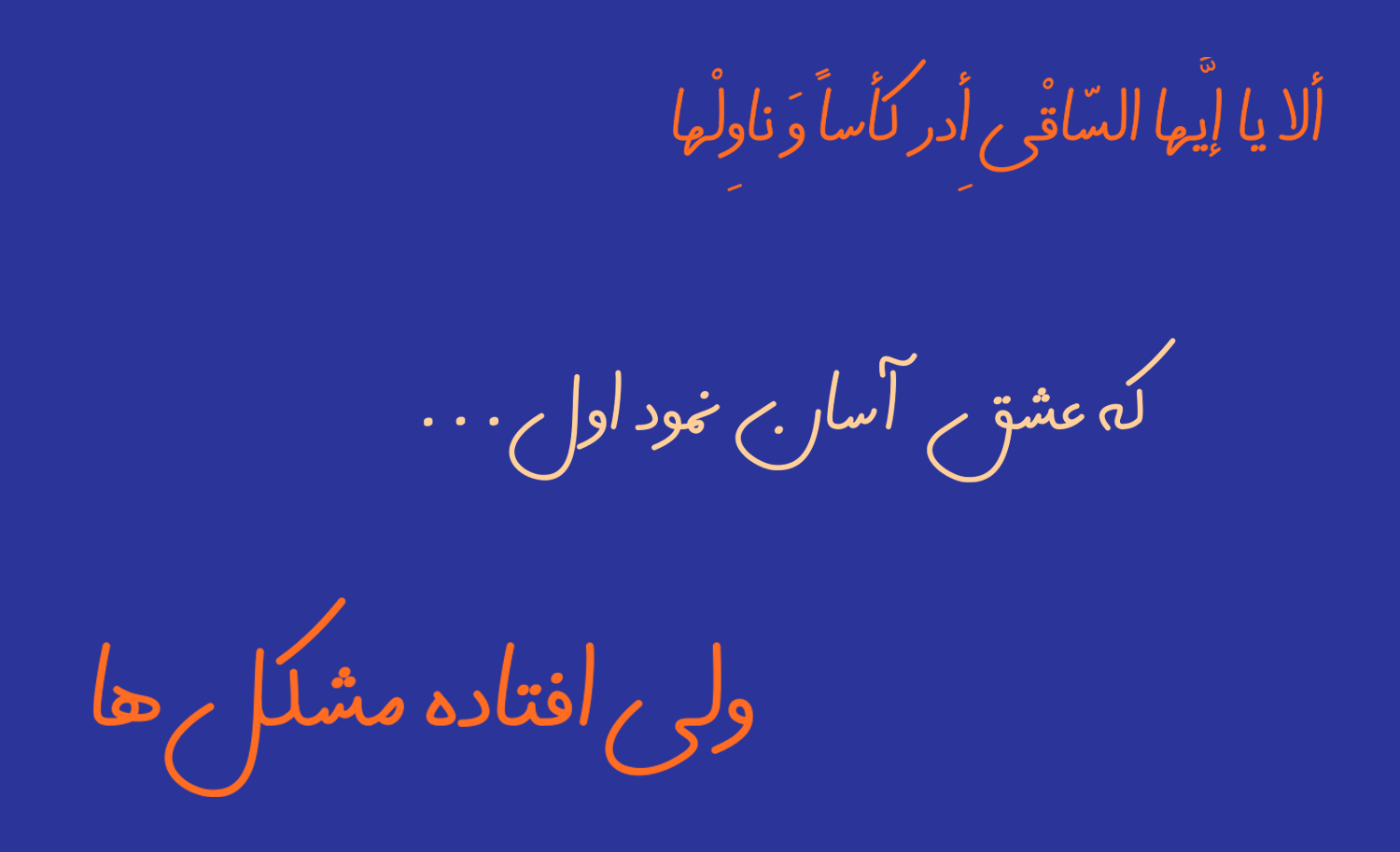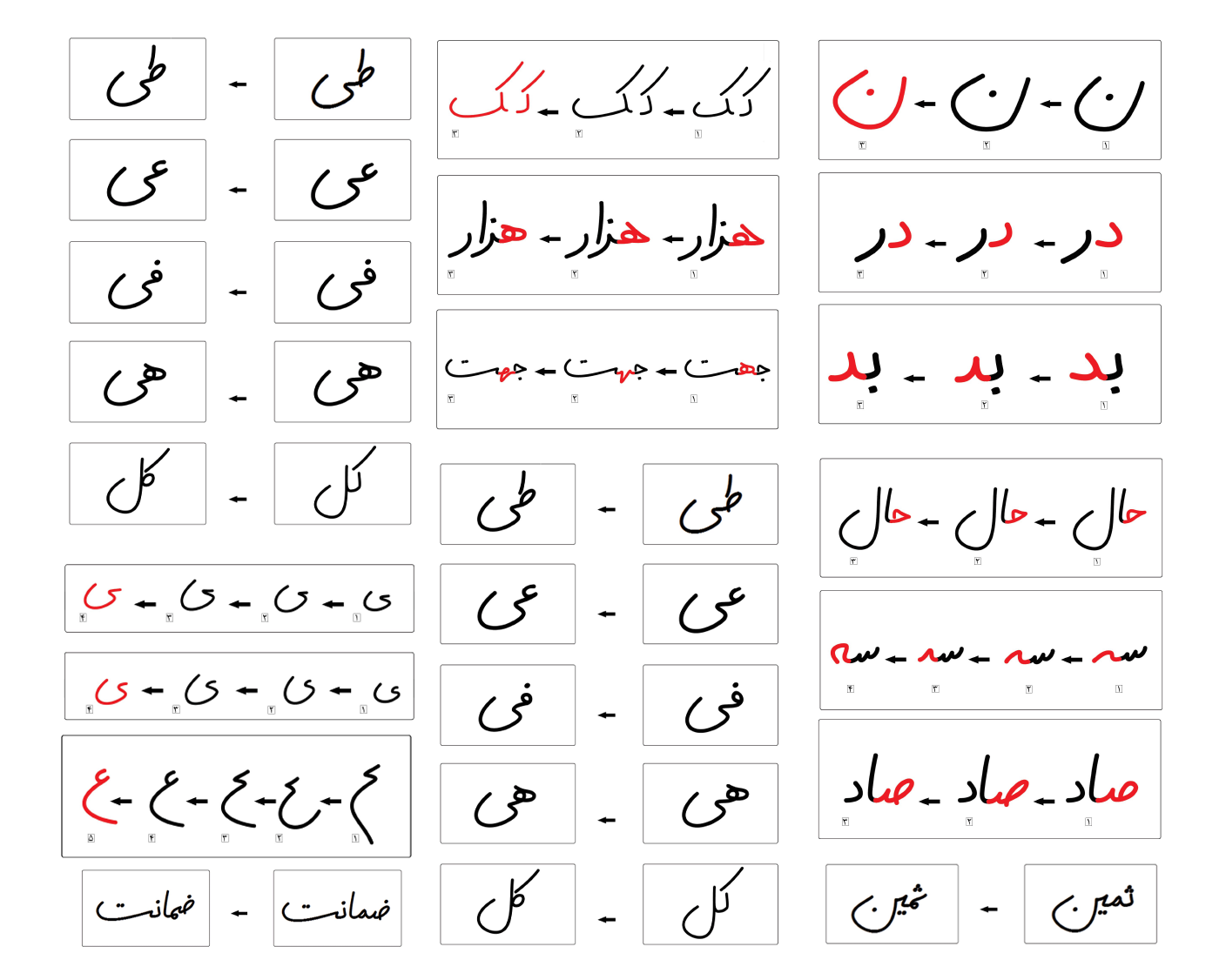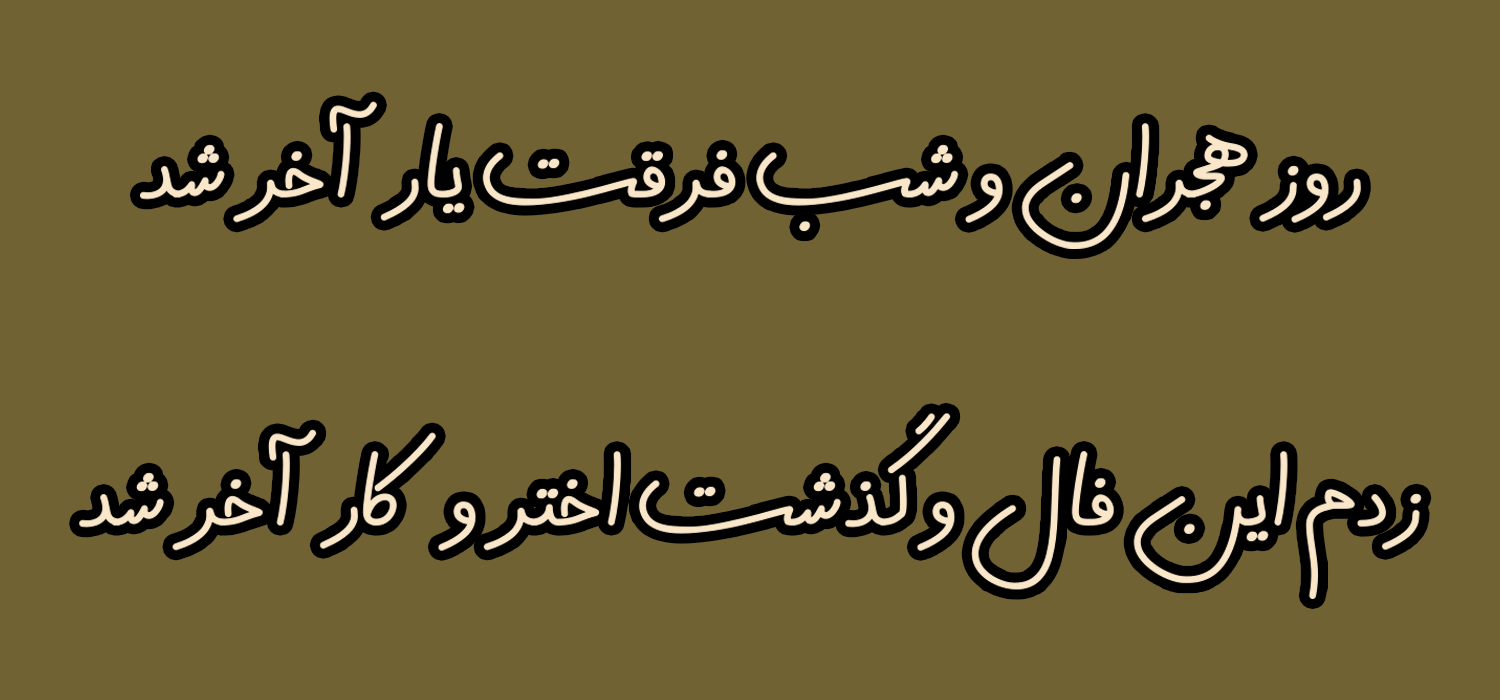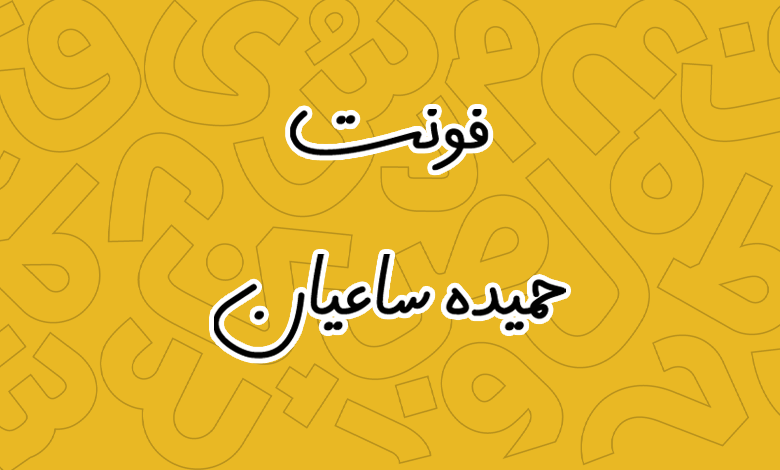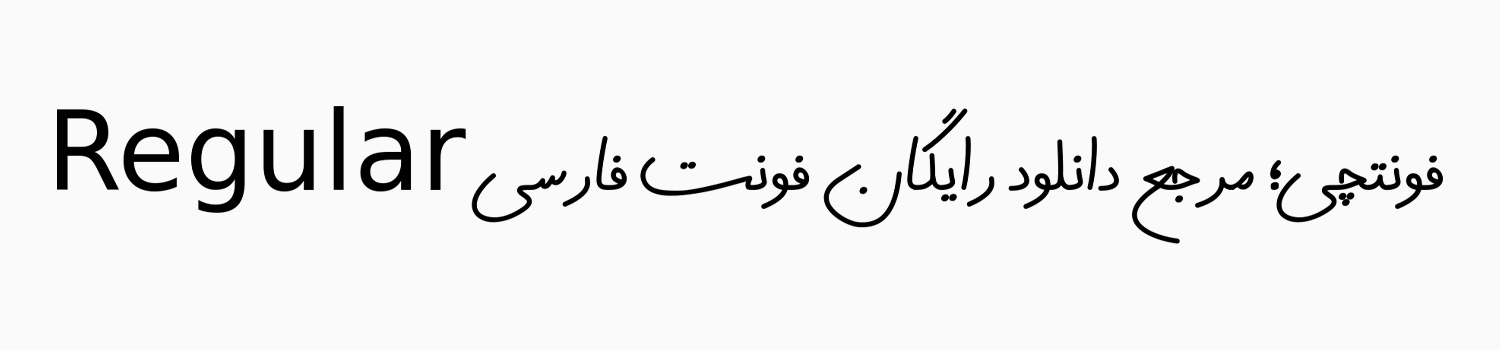
فونت حمیده ساعیان (Hamideh Saeian)
فونت حمیده ساعیان (به انگلیسی: Hamideh Saeian) در گروه فونت دست نویس قرار دارد که می‌توانید از آن برای متن‌های طولانی استفاده کنید. این قلم را همچنین می‌توان در گروه فونت خودکار نیز طبقه‌بندی کرد، چرا که بر اساس دست‌خط شخصی طراحی شده است.
حمیده ساعیان این قلم را بر اساس دست‌خط شخصی خود طراحی کرده که در مقایسه با سایر فونت‌های دست نویس خودکاری، آزادی شکل و تنوع بیشتری به حروف و ترکیبات را در این قلم پیاده‌سازی کرده است که می‌تواند برای استفاده‌های تبلیغاتی، فرهنگی و هنری، فضاهای صمیمی و شاعرانه کاملا ایده‌آل باشد.
در ادامه این نوشته از سایت فونتچی به نقد و بررسی کامل فونت حمیده ساعیان خواهیم پرداخت؛ قلمی به سبک دست نویس خودکاری که در یک وزن معمولی Regular در دسترس بوده و می‌توانید از آن در انواع نرم‌افزار گرافیکی و ویرایشگر متن با پشتیبانی کاملی که از دو زبان فارسی و عربی دارد استفاده کنید.
جدایی از اینکه این فونت، یک قلم صمیمی و بر اساس دستخط شخصی است؛ شکل خاص و آزادی که به حروف در این قلم داده شده آن را به گزینه‌ای عالی برای فضاهای تبلیغاتی بدل کرده است. امکان استفاده از ترکیبات متنوع برای حروف سبب می‌شود تا بتواند برای نکته نویسی در تبلیغات انتخاب خوبی باشد.
سبک طراحی و وزن فونت ساعیان
در این فونت طراح بر اساس دستخط شخصی خود ابتدا حروف را طراحی کرد و سپس به منظور نمایشی و زیباتر کردن تمامی حروف و ترکیبات سعی شده تا از خوشنویسی به روح این قلم دمیده شود که انصافا خوب هم عمل کرده است.
با این کار شکل حروف از حالت خامی خارج شده و جدایی از اینکه فرم حروف به بهترین شکل پیاده‌سازی شده است، موجب نرم‌تر شدن و صمیمی تر شدن ساختار کلی قلم شده است.
پشتیبانی کامل از دو زبان فارسی و عربی
فونت ساعیان از دو زبان فارسی و عربی پشتیبانی تقریبا کاملی دارد. تمامی حروف که به صورت مشترک در این دو زبان قرار دارند در آن پیاده سازی شده است و شکل استاندارد هم را دارند.
اما حروفی که در زبان عربی متفاوت از زبان فارسی است، مانند «ک، ی، ه، ؤ، ئ» دارای گلیف اختصاصی خود هستند که هنگام استفاده از زبان عربی این ظاهر متفاوت روی حروف اعمال و تایپ می‌شود.
اعراب نیز در هم‌نشینی درستی با سایر اعراب همچون همزه، تشدید و سکون قرار دارند که نه به حروف قبل و بعد می‌چسبند و نه اینکه فاصله آنها در هنگام استفاده ترکیبی در تضاد زیادی با یکدیگر قرار دارد.
در بخش اعداد نیز این فونت با اینکه یک فونت دست‌نویس و بر اساس دستخط شخصی طراح است، اعداد فارسی و عربی را به شکل جداگانه پشتیبانی نمی‌کند. برای زبان فارسی به جای شکل استاندارد اعداد «۴۶» از شکل عربی آن یعنی، «۴۶» استفاده شده است و در مقابل برای عربی نیز به جای عدد «۵» از حالت فارسی آن یعنی «۵» استفاده شده است.
زبان انگلیسی در این فونت دارای طراحی دست نویس نبوده و از همان ساختار معمولی برای حروف لاتین استفاده می‌شود که پیشنهاد می‌کنیم از طریق صفحه فونت دست نویس انگلیسی فونت دیگری را در صورت استفاده ترکیبی از دو زبان در متن خود در نظر بگیرید.
دارای حروف و ترکیبات جایگزین بسیار متنوع
ویژگی متمایز این فونت در مقایسه با سایر فونت‌های دست نویس که ساختاری خودکاری دارند، پشتیبانی از حروف و ترکیبات جایگزین بسیار متنوع است که امکان تایپ کلمات را در چند حالت مختلف فراهم می‌کند. چنین ساختاری را پیش از این در فونت مانلی مشاهده کرده‌ایم.
همانطور که در تصویر بالا می‌بینید این‌ها تنها بخشی از ترکیبات و حروف جایگزین فونت ساعیان هستند که می‌توانید از طریق تنظیمات Open Type نرم افزار گرافیکی از آنها استفاده کنید. ترکیبات متعدد دیگری نیز در این فونت پیاده‌سازی شده که با استفاده از تنظیمات این بخش می‌توانید پیش‌نمایش آنها را در نرم‌افزارهای قابل پشتیبانی مشاهده و استفاده کنید.